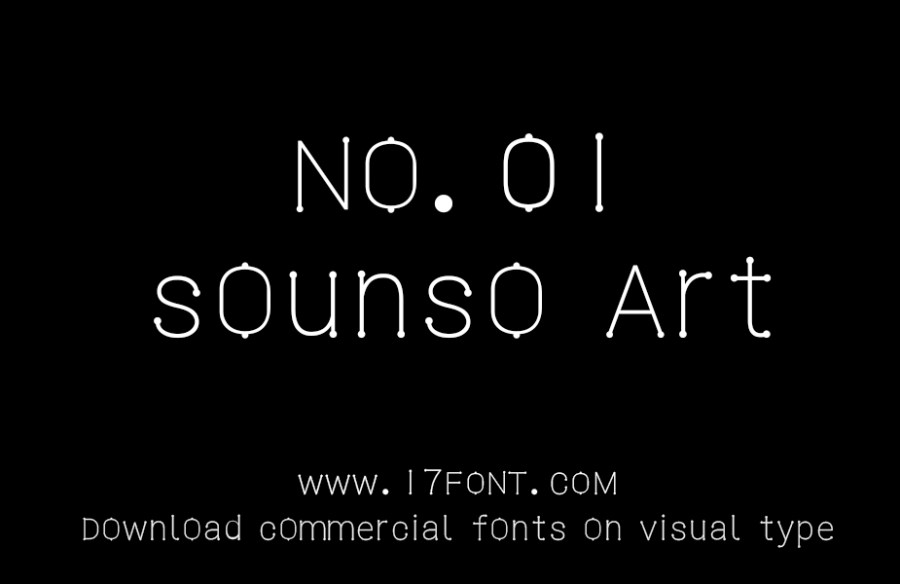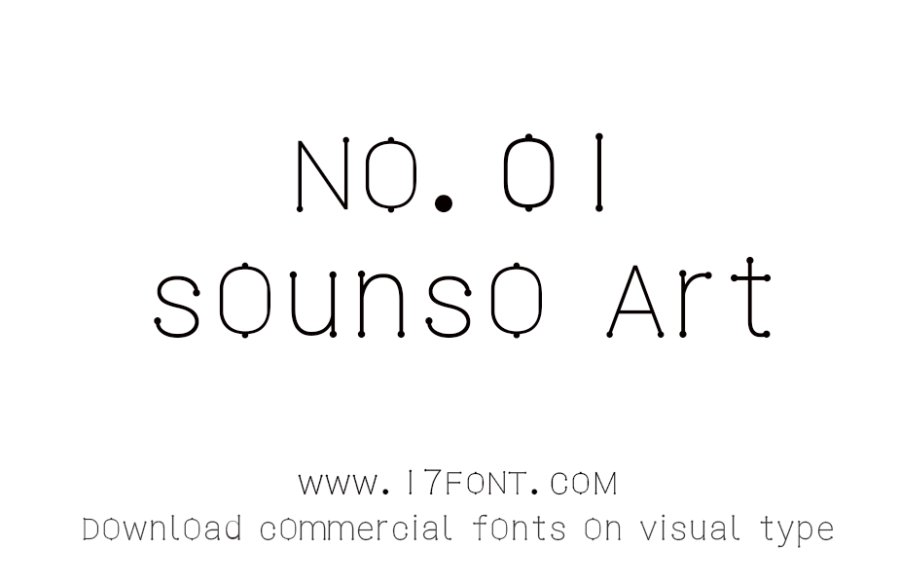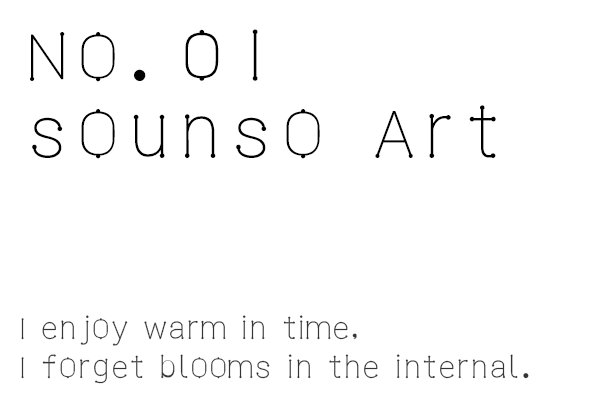
笔画柔润,在英文首尾或交界处添加了实心圆形,呈现出似火柴的形态,整体体型纤细,横竖粗细均匀。可以用于英文广告设计、品牌设计、产品包装等高端属性上,效果非常不错。购买须知:“下载服务费”与“字体VIP”所获得字体 仅用于个人非商用, 商用请联系付费授权。本字体为电脑用字,手机没有root权限不支持直接手机换字(手机如何root,请自行百度搜索教程)。购买前请先 了解清楚后再付款 ,字体为虚拟产品无法回收 一旦购买不支持退款。